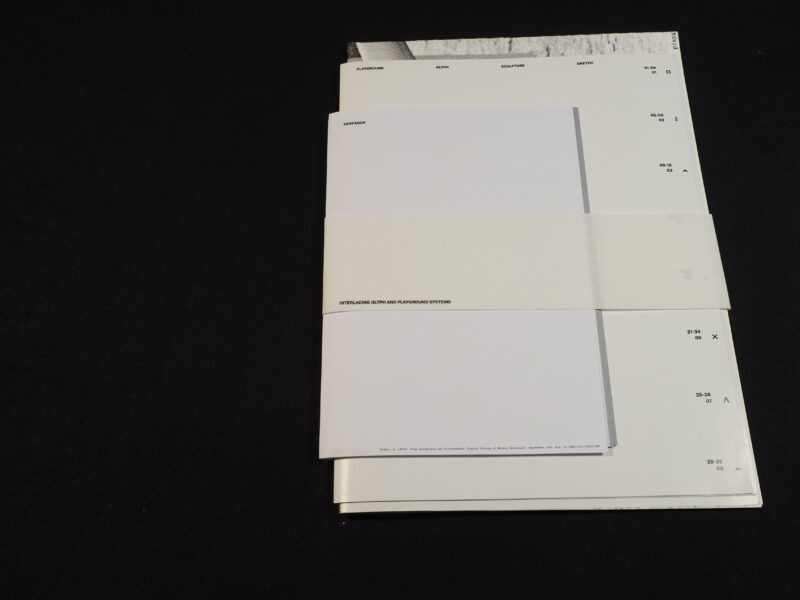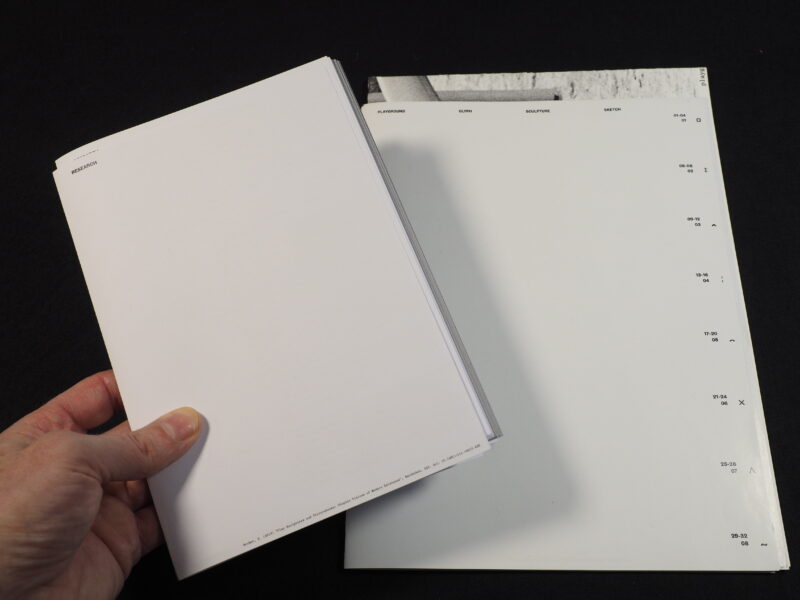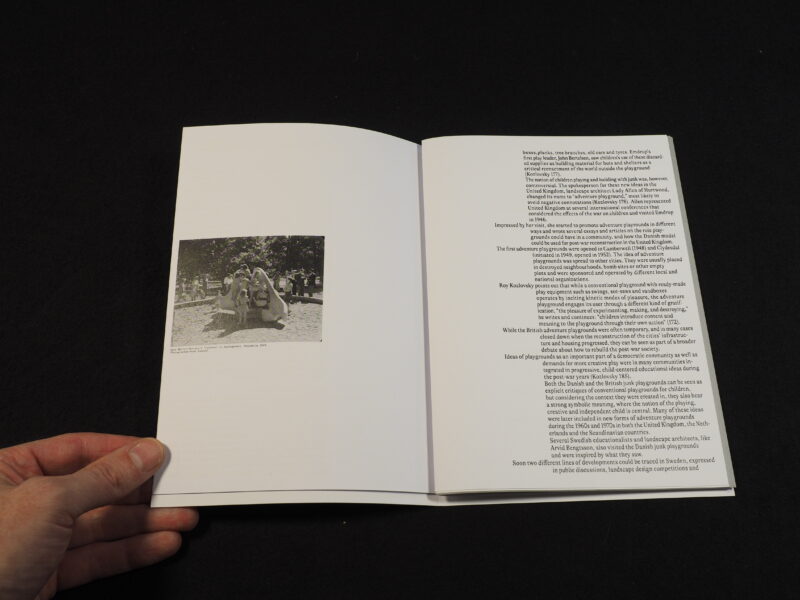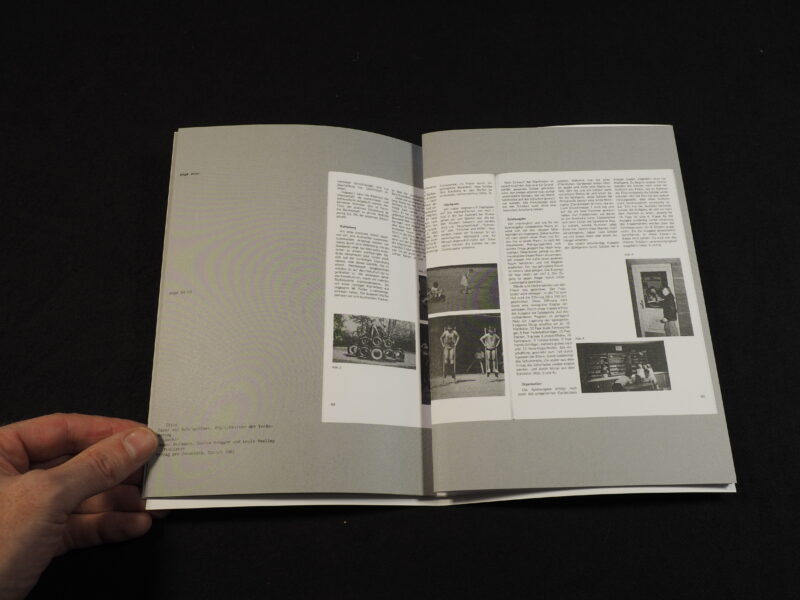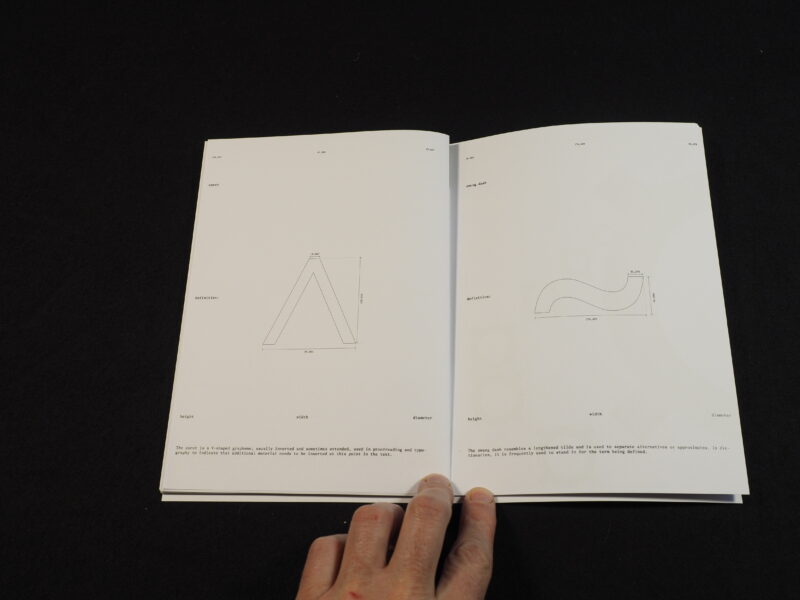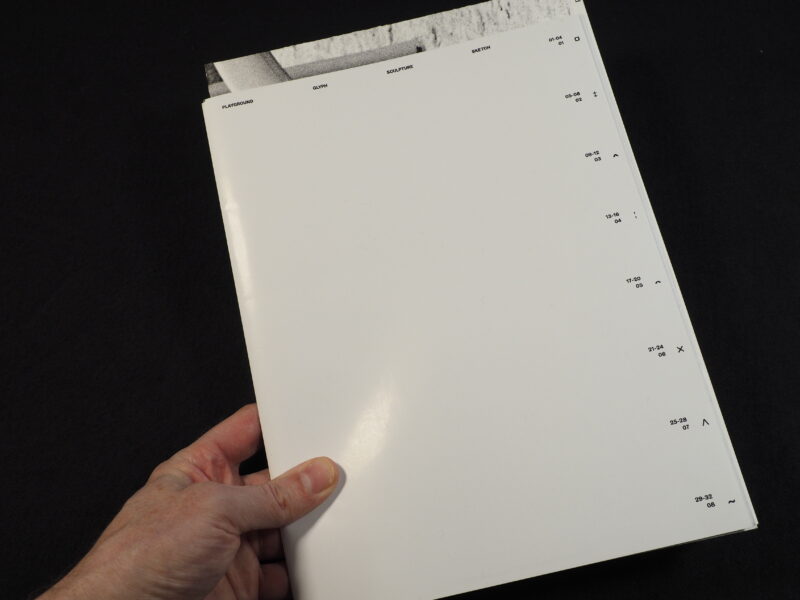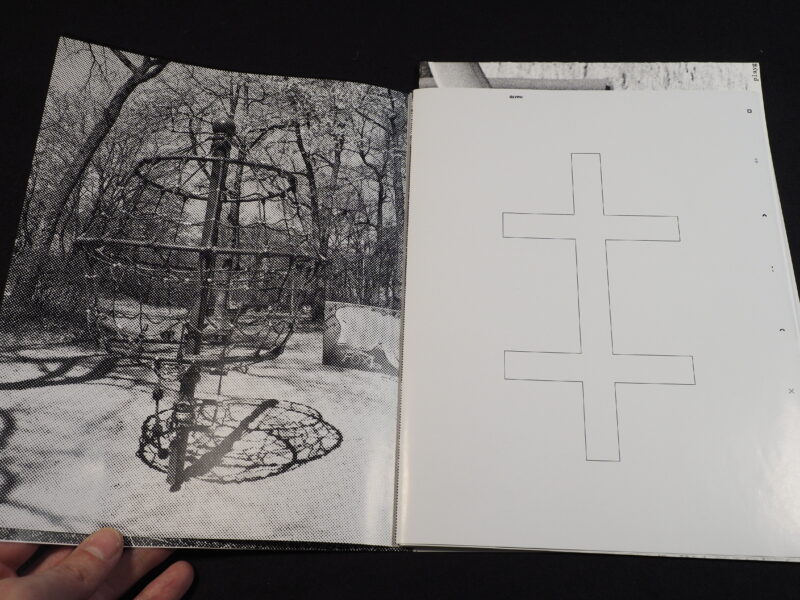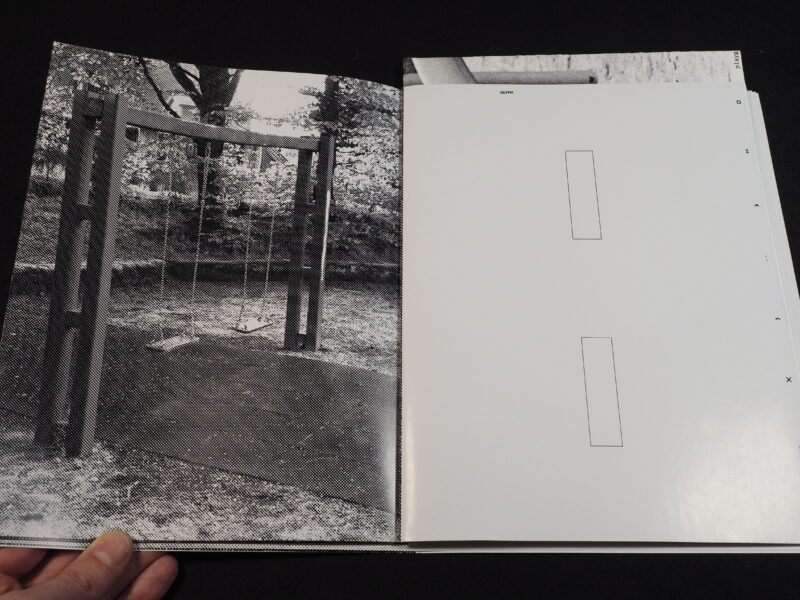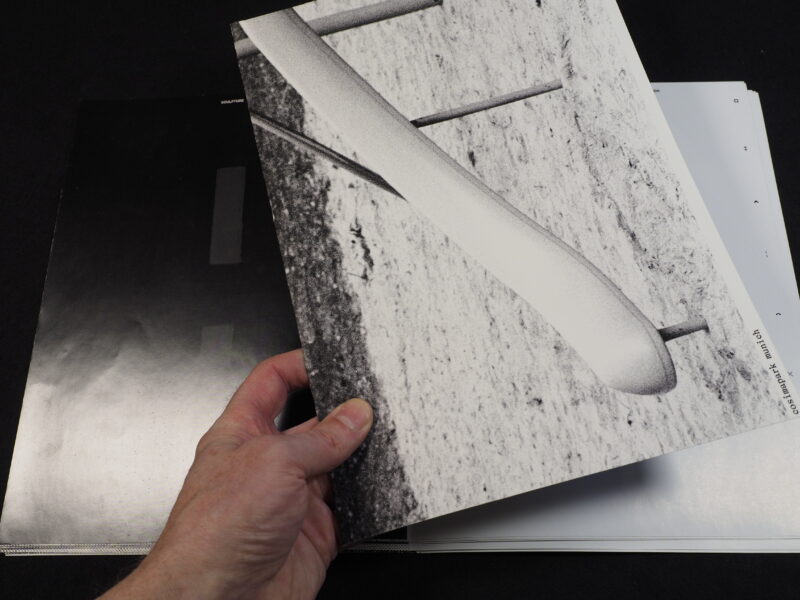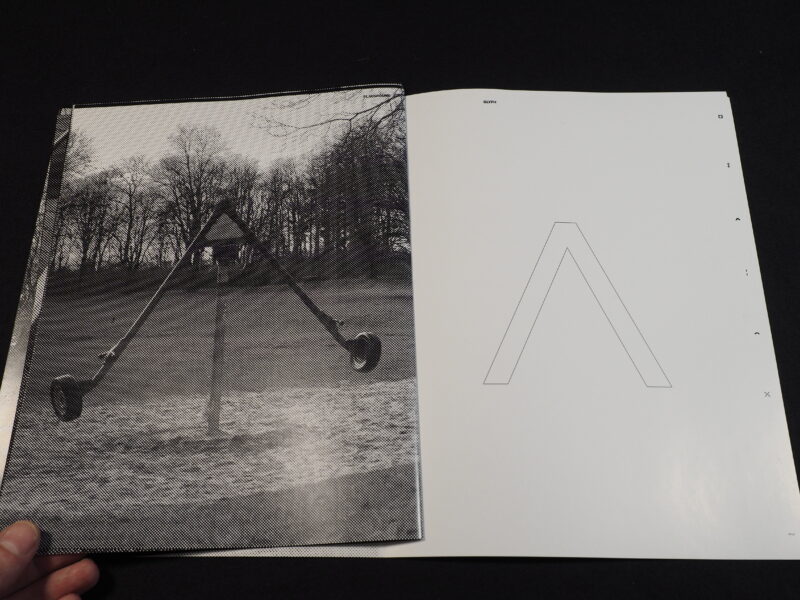
Playground
Das Interesse an Spielplätzen, Playgrounds, resp. an Spielplatz-Geräten und ihrem Design bildet das Fundament der Auseinandersetzung. In einem ersten Schritt wurde auf diesem Gebiet recherchiert und eine umfangreiche Dokumentation angelegt. Daneben entstanden Fotografien von Spielplatz-Gerät. Parallelen von Gerätschaften zu Schriftzeichen drängten sich auf. Die Hauptarbeit bestand in der Organisation und Gestaltung der Dokumentation.